2016 타이포 베를린 Typo Berlin
타이포 베를린은 모든 디자인과 타이포그래피를 다루는 독일의 세계적인 컨퍼런스로, 올해는 ‘타입 너머(beyond type)’라는 주제로 꾸려졌다.
2016 타이포 베를린 (Typo Berlin 2016)
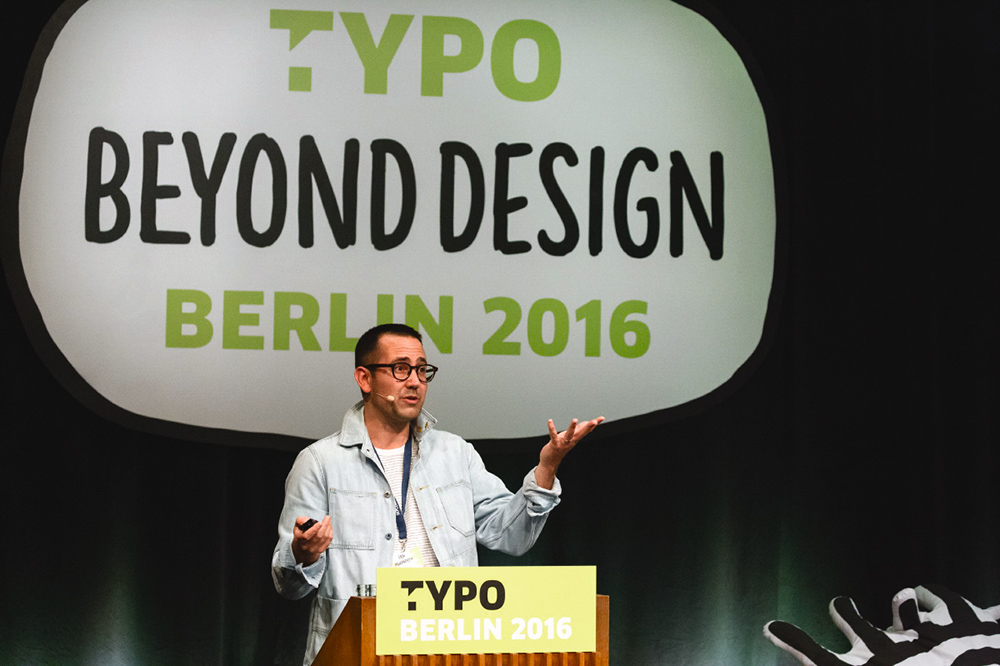
“지금이야말로 레터링, 타입 디자인 그리고 캘리그래피에 관심을 가질 최적의 시기입니다.” – 에릭 마리노비치
첫 번째 강연은 디자인 경영자(Design Executive Officer)의 약자인 DEO를 중심으로 진행되었는데, 오토데스크의 부회장 마리아 주디체는 “DEO란 무엇일까?”란 질문을 시작으로 DEO를 크리에이티브 사업의 경영자로 정의하면서 강연을 시작했다. 그녀는 이 직업을 구성하는 핵심적인 요소는 위험을 감수하는 역할이라고 언급하면서 이와 같은 모험은 유익한 것이라고 주장한다.
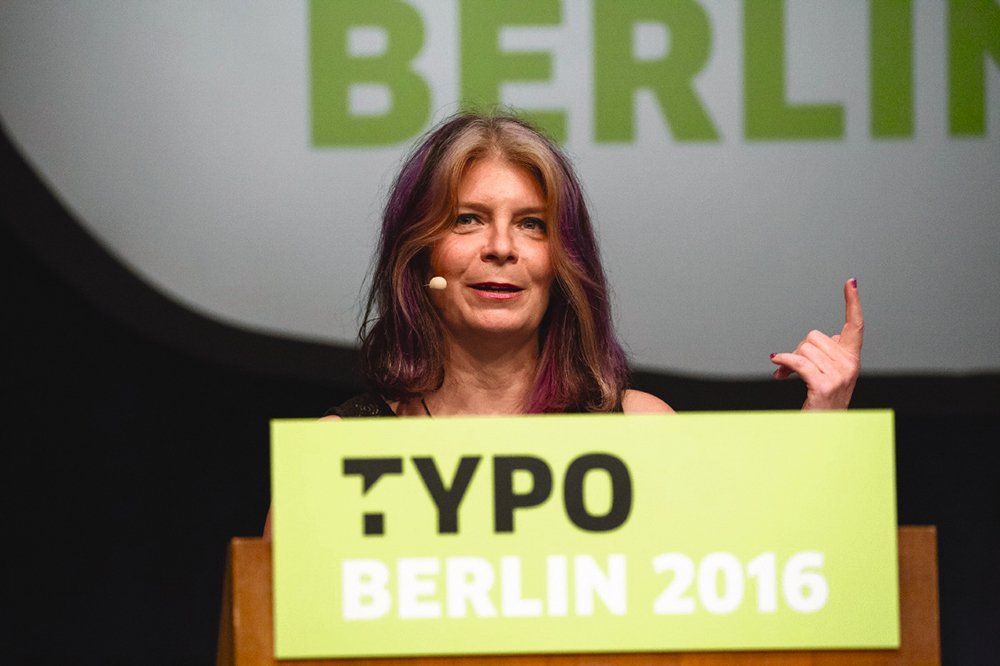
마리아 쥬디체가 위험을 감수하는 것에 대해 말한다.
모험과 위험에 관한 견해는 2016 타이포 베를린에서 반복적으로 등장했는데, 특히 런던의 디자인 스튜디오 필드의 공동 창립자인 마르쿠스 벤트(Marcus Wendt)와 베라 글란(Vera Glahn)의 강연에서 두드러졌다. 이들은 관객을 시청각의 모험에 초대하면서 혼란, 영감, 흥분, 무지와 두려움을 거치는 창의성의 순환과정에 대해 이야기했다.
“창의성이 필요한 작업은 종종 혼란에서 출발하죠.” 벤트가 곰곰이 생각하며 말한다. 그는 디젤이 뉴욕에 새롭게 개장하는 플래그십 스토어를 위한 영상 프로젝트를 진행하던 당시를 회상하며 의심과 두려움이 가득했다고 언급한다. 이 프로젝트는 위험성이 매우 컸다. 빛 한 점 없는 어둠 속에서 웨일스의 늪지를 느릿느릿 건너며 비싼 임대 장비를 끌고 가야 했기 때문이다. 벤트는 그들이 의도한 장면을 완성할 수 있을지 확신이 없었다. 결과적으로 그들은 이 프로젝트를 완벽하게 해냈고, 다음 프로젝트를 하와이에서 진행하자는 제안을 받았다.
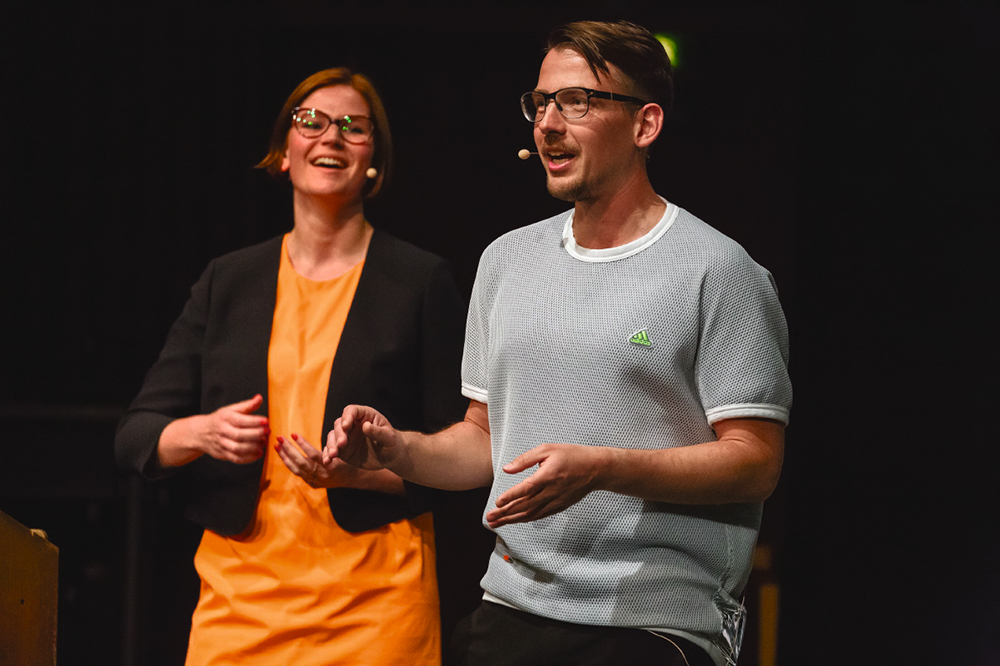
필드 설립자 베라 마리아 글란과 마커스 벤트
벤트는 모험을 위해선 새로운 영역을 개척할지라도 자신의 경험을 신뢰하고 창의적 공정에 믿음을 가져야 한다고 설명한다. “때때로는 아직 미숙한 아이디어를 던져놓고, 다른 분야에서의 경험이 자신을 이끌어주기를 바라는 거죠. 어떻게 해야 할지 그 방법을 모른다는 것이 흥미로운 점이에요. 겁먹지 마세요. 일단 전념하고 나면 좋은 결과가 나타나기 마련이니까요.” 글란이 덧붙인다.
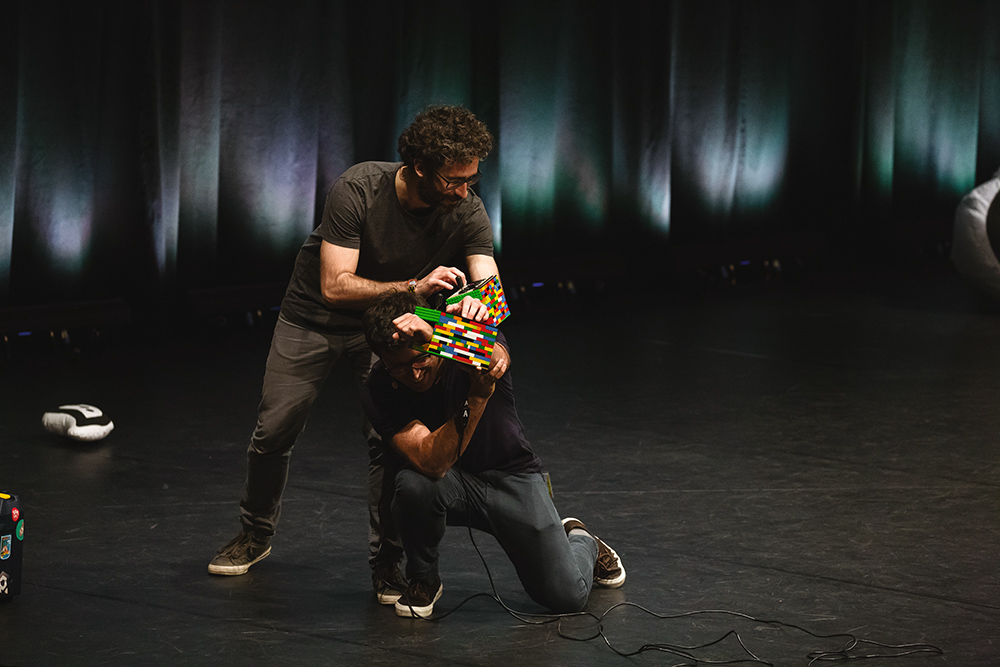
브로스마인드(BROSMIND)는 온 몸을 사용하고 있다
LA의 타입 디자이너 데이비드 조나단 로스(David Jonathan Ross)는 아주 흔한 현상인 로마자의 세로쓰기를 논의했다. 그는 세로짜기를 위한 유채색의 서체 번지(Bungee)를 만들었다. 로마자의 세로쓰기에 너무 많은 시간을 투자하는 것에 찬성하지 않으면서도 그는 어떤 분야라도 실험에 뛰어드는 것이 중요하다고 언급한다.
“흥미롭고도 흔치 않은 문제를 해결하면 결국 흔치 않고 흥미로운 해결방안을 얻게 되는 거죠.” 그가 말한다. 그러나 이번 행사에서 모험에 관해 가장 잘 표현해낸 사람은 여전히 벤트와 글란일 것이다. “당신이 꿈에 그리던 아이디어를 실현할 용기가 없다면, 어떤 사람이 당신에게 자신의 아이디어를 믿고 맡기겠습니까?”
일시: 2016년 5월 12일-14일
장소: 독일 베를린
주요 연사: 조나단 반브룩(JONATHAN BARNBROOK), 토비아스 프레레 존스(TOBIAS FRERE-JONES), 나딘 샤힌(NADINE CHAHINE), 미스터 빙고(Mr Bingo), 에릭 마리노비치(ERIK MARINOVICH), 필드(FIELD), 마리아 주디체(MARIA GIUDICE) 등